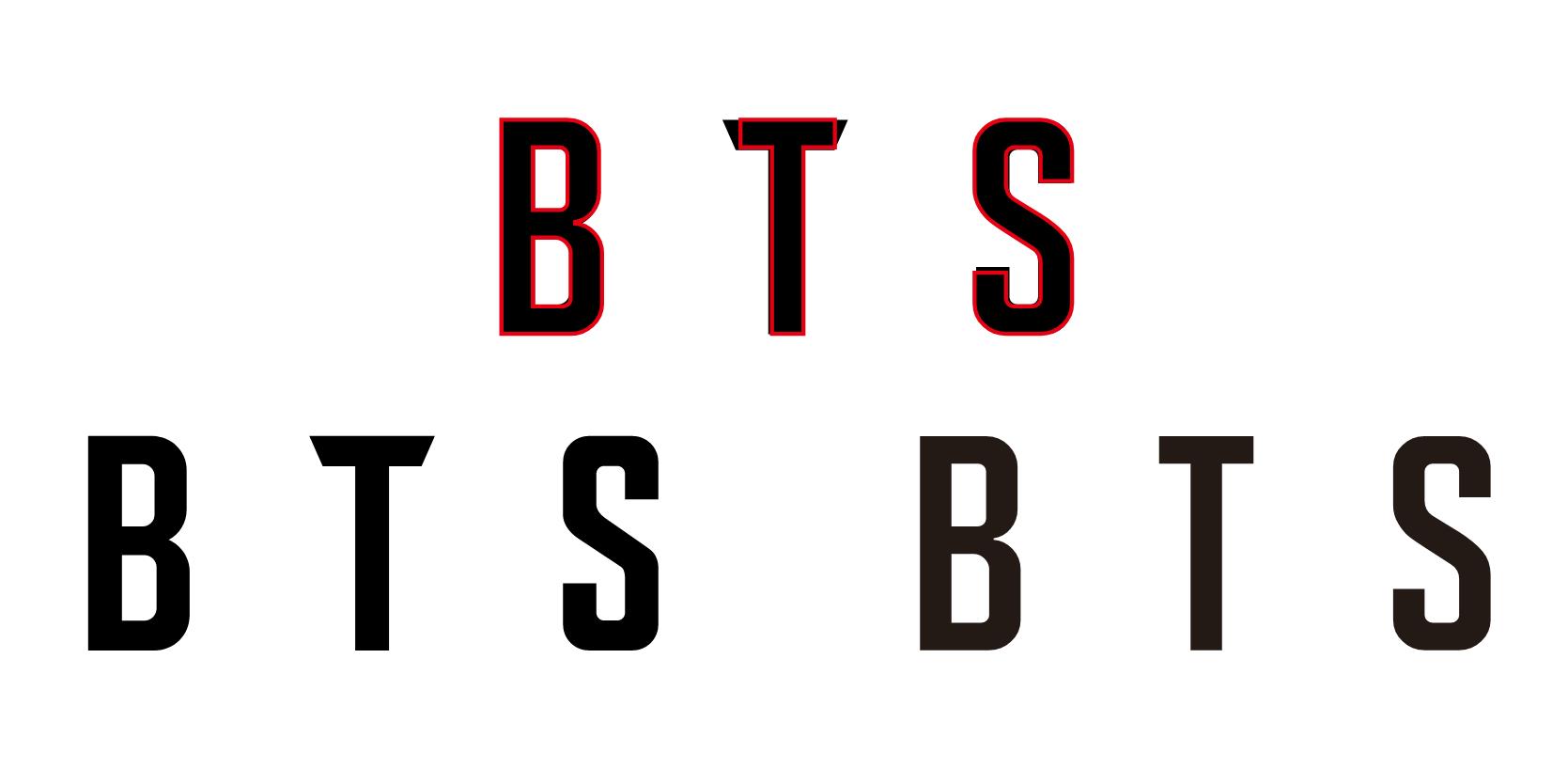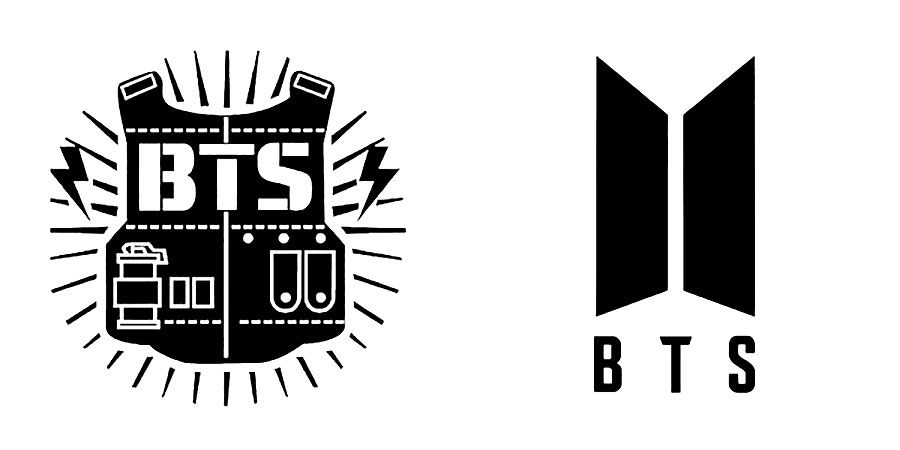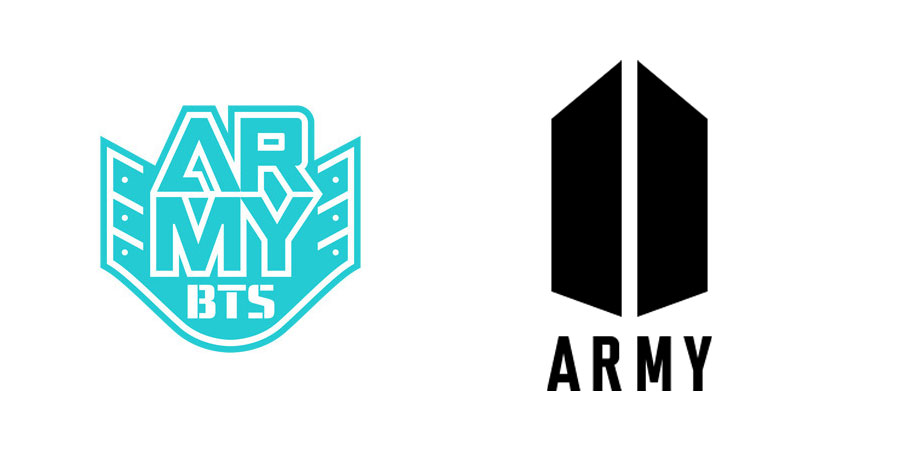
BTS(방탄소년단)는 2013년 6월 13일에 데뷔한 우리나라 7인조 보이그룹입니다. 멤버는 진, 슈가, 제이홉, RM, 지민, 뷔, 정국 7명 으로 구성되어 있습니다.
BTS는 데뷔 초기에 방탄소년단(防彈少年團)이란 이름으로 활동을 시작했습니다. 총알을 막아낸다는 의미의 '방탄'은 10대들이 살아가면서 겪는 힘든 일, 편견과 억압을 우리가 막아내겠다는 심오한 뜻이 있다고 합니다. 세계로 활동 무대를 넓혀가면서 방탄소년단이라는 이름보다 약어인 BTS로 알려졌는데, Bang Tan Sonyeondan 혹은 Bang Tan Scout을 BTS라고 줄여서 부르기도 하는데, BulleTproof BoyS라는 뜻도 있습니다. 로고를 바꾼 이후 Beyond The Scene이라는 뜻을 더해 최근에는 이 뜻으로 많이 사용됩니다.
초기 BTS 로고와 2017년 리뉴얼된 현재의 로고
초기 로고는 말 그대로 '방탄'을 강조하여 방탄조끼 모양에 BTS 타이포를 더하여 디자인 되었습니다. 리뉴얼된 현재의 로고는 2017년 7월에 공개되어 상당한 호평을 받았으며, 2018년 2월에 세계 3대 디자인 어워드 중 하나인 독일 'iF Design Award'에서 본상을 수상하기도 했습니다.
단순화된 방탄조끼 이미지와 열리는 문 이미지를 더해 간결하고 세련되게 바뀐것이 '신의 한 수'급 리뉴얼 같습니다.
'아미'는 BTS의 공식 팬클럽 이름으로 팬카페 회원수가 138만명에 이를 정도로 엄청난 규모를 자랑합니다.
'아미'는 ARMY 군인을 뜻하며 방탄조끼와 군인이 항상 함께하듯이 BTS와 항상 함께한다는 의미를 가지고 있습니다.
예전의 아미(A.R.M.Y) 로고와 리뉴얼된 로고
초기의 로고는 BTS 초기로고와 같이 방탄조끼 디자인이었는데, BTS 로고가 리뉴얼되면서 동일한 폰트와 문이 앞을 향해 열리는 듯한 디자인으로 변경되었습니다.
BTS 로고에 사용된 폰트는?
공식적인 BTS 로고에 사용된 폰트는 알려지지 않았습니다. 다만, Solano Gothic MVB bold 폰트가 BTS 로고와 유사한 것으로 보아 이 폰트를 변형하여 로고를 제작한 것으로 추정됩니다.
BTS 로고와 Solano Gothic MVB bold 폰트의 비교